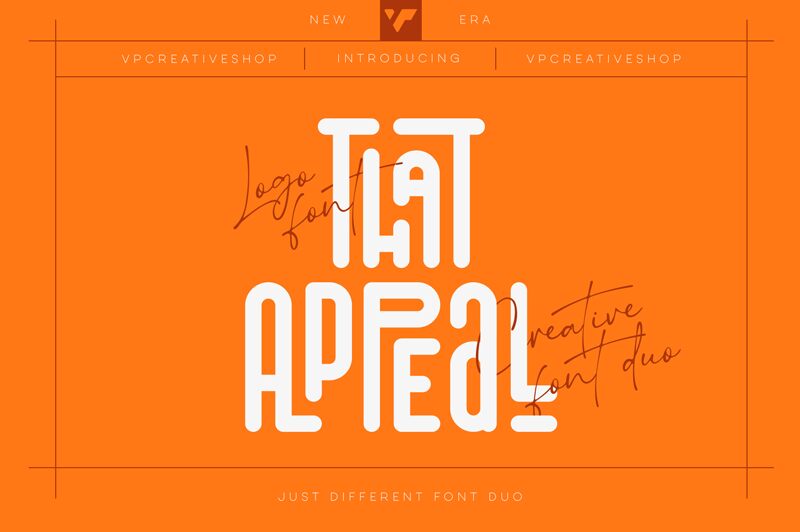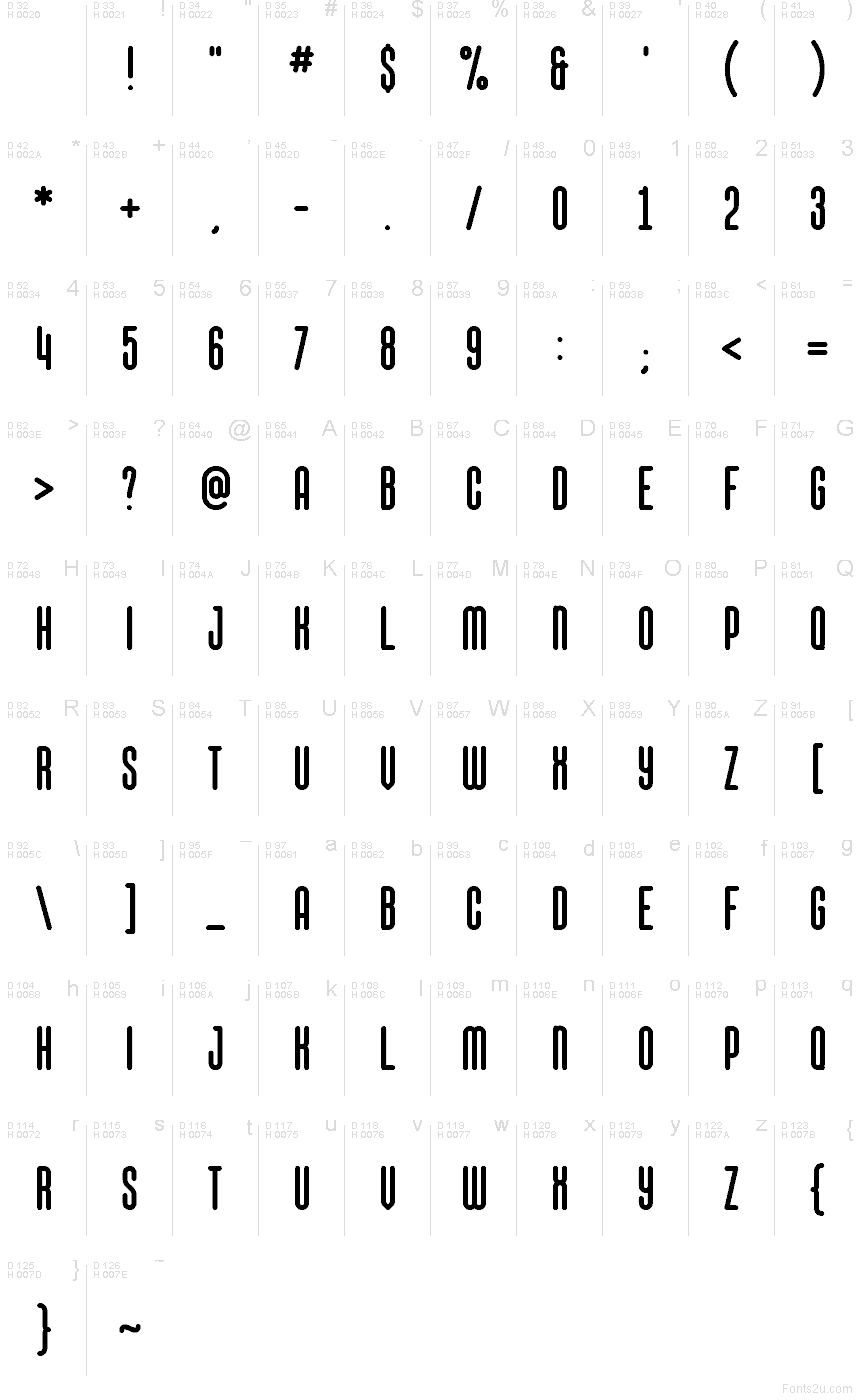
That Appeal Free Demo
Die kostenlose Schriftart That Appeal ist eine hohe, schmale, serifenlose Schrift mit abgerundeten Enden, fließenden vertikalen Linien und einem straffen, aufrechten Rhythmus, der ihr eine klare, präzise Formensprache verleiht. Die Buchstaben wirken schlicht und direkt, mit einer einheitlichen Struktur, die die Wortbilder kompakt hält, ohne dabei starr zu wirken.
That Appeal eignet sich hervorragend für Logogestaltungen, Plakatüberschriften, Verpackungen, Albumcover, Beschilderungen und Einladungskarten, bei denen kurzer Text eine starke vertikale Linie benötigt. Dank ihrer schmalen Formen und abgerundeten Ecken fügt sie sich perfekt in begrenzte Räume ein und bewahrt dabei stets einen sauberen, grafischen Look.